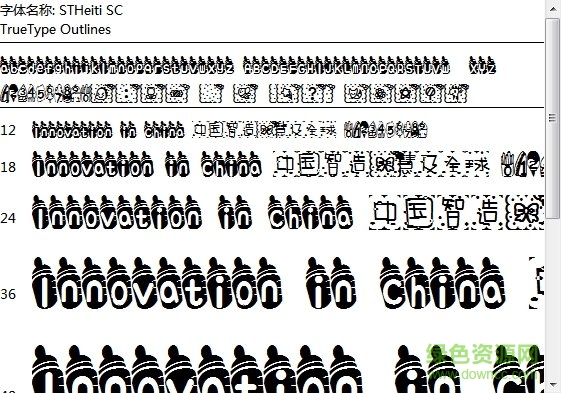
软件介绍 软件标签: 巧克力字体 pop字体 巧克力精灵字体是一款从手机字体中提取出来的个性卡通字体,字迹流畅有着多样的点缀与装饰,让文字更加清新,如巧克力的香甜,绿色资源网诚意推荐!巧克力字体介绍巧克力字体有着浓郁的巧克力香气,给文字增加了独特的美感,深受小女生和小孩子们的喜欢,可以广泛运用在艺术设计、平面设计、广告设计等诸多领域当中。巧克力精灵字体ttf安装针对win7系统,用户只需选中字体右键安装即可。其他系统直接将字体复制到C:WINDOWSFonts。或者在控制面板/字体/文件/安装新字体。 暂提供同类字体下载! 软件截图 上一张下一张(1 / 1) 安装详细截图 其他版本下载 标题 大小 更新日期 下载 下载地址 电脑版 巧克力精灵字体 点击报错 软件无法下载或下载后无法使用,请点击报错,谢谢! 关闭报错反馈 请描述您所遇到的错误,我们将尽快予以修正,谢谢! *必填项,请输入内容 本类最新 dreamweaver字体库 首尔南山体字体 v1.06 官方版 潮字社风云简ttf 潮字社凌渡鲲鹏简体字体 潮字社曾玉波手书简字体 微博慧心字体 相关文章 Photoshop字体安装使用方法和技巧 Win 7系统安装字体方法 网页字体大小设置方法 怎么改网页字体大小 在Linux系统中安装字体的几种方法 windows7字体显示问题:打开某些程序的时候显示的是乱码 Windows7安装字体和用快捷方式安装字体 用户评论 热门评论 最新评论 发表评论 查看所有评论(0) 昵称: 请不要评论无意义或脏话,我们所有评论会有人工审核. 字数: 0/500 (您的评论需要经过审核才能显示)